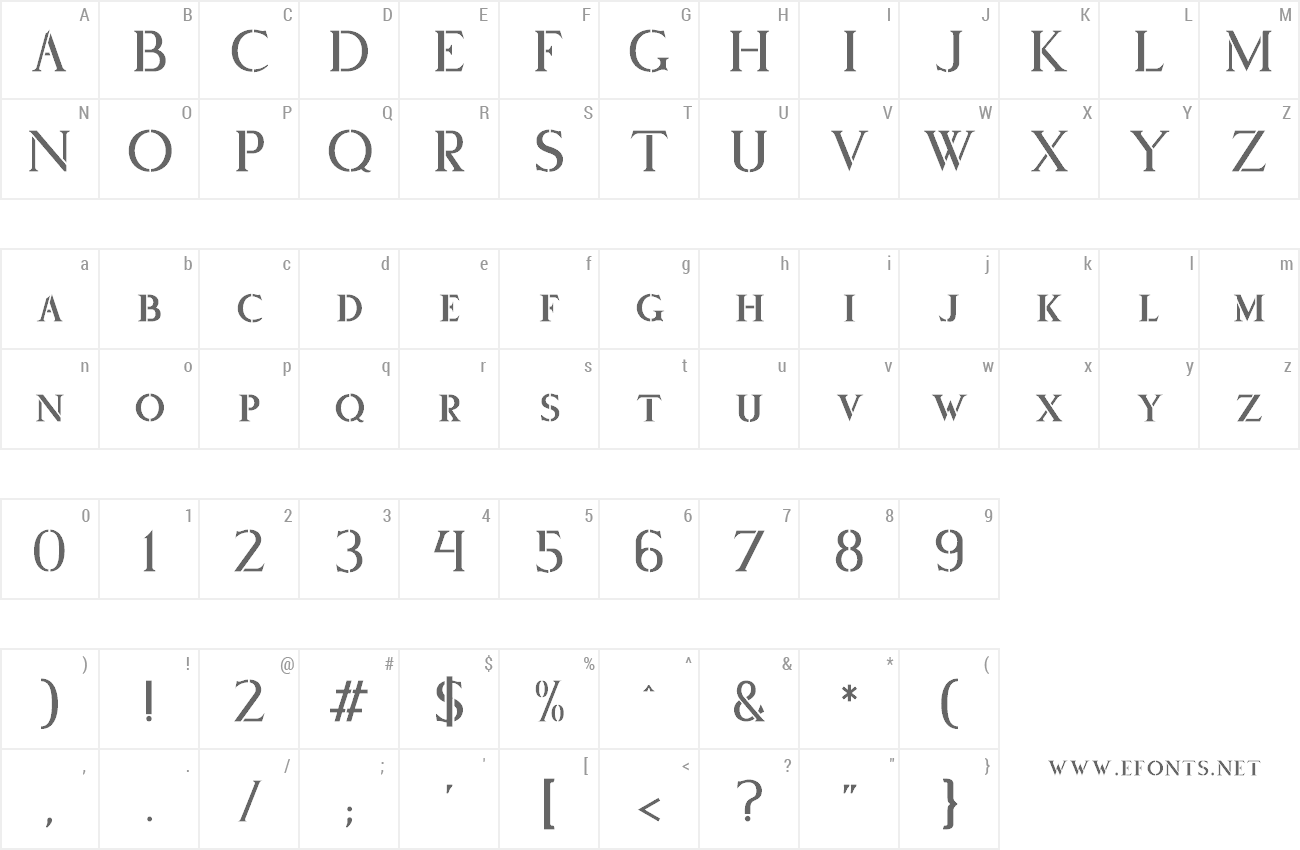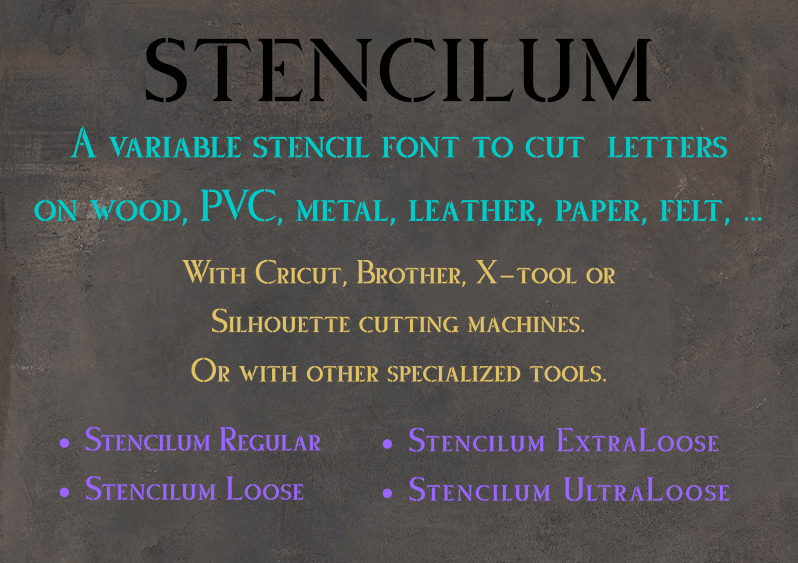
Une police variable � utiliser avec des machines � d�couper (Cricut, Brother, X-Tool, Silhouette). Pour d�couper des lettres sur bois, m�tal, PVC, cuir, papier, feutre, etc. Ou avec d'autres logiciels sp�cialis�s. A variable font to cut letters on wood, PVC, metal, leather, paper, felt, etc. With the Cricur, Brother, X-Tool or Silhouette machines. Or with other specialized softwares. |